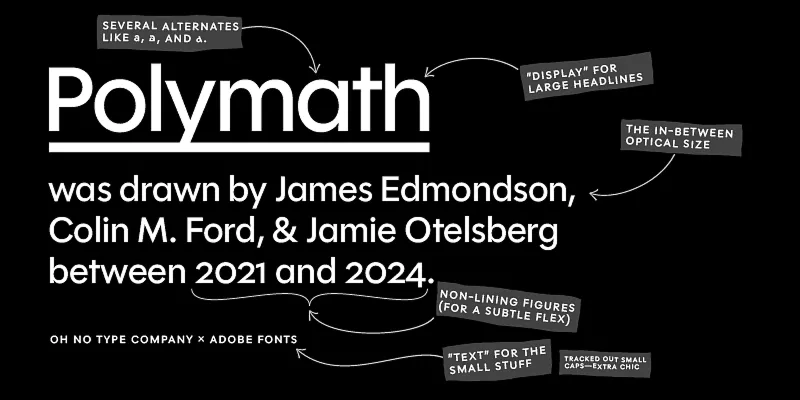
Font Tiếng Việt Polymath Black Font
Font Tiếng Việt Polymath Black Font – Font Đậm Mạnh Mẽ Cho Thiết Kế Nổi Bật
Polymath Black Font là lựa chọn cực kỳ phù hợp nếu bạn đang tìm một font chữ tiếng Việt dạng đậm (black) với phong cách hiện đại, cá tính và có độ “nặng” vừa đủ để tạo điểm nhấn mạnh cho tiêu đề. Nhờ nét chữ dày, chắc và đầy năng lượng, Polymath Black thường được dùng trong các dự án thiết kế cần gây ấn tượng nhanh như poster, banner quảng cáo, bìa mạng xã hội, hoặc nhận diện thương hiệu.
Polymath Black Font là gì?
Polymath Black là biến thể “Black” – tức độ đậm cao nhất trong hệ font, giúp chữ hiển thị rõ ràng ngay cả khi đặt trên nền phức tạp hoặc khi thu nhỏ trên các thiết kế digital. Font phù hợp khi bạn muốn:
• Tạo tiêu đề nổi bật trong poster/cover
• Thiết kế banner quảng cáo, thumbnail YouTube
• Làm logo chữ, slogan, headline landing page
• Dùng cho social content cần sự mạnh mẽ và rõ nét
Ưu điểm nổi bật của Font Tiếng Việt Polymath Black
• Nét chữ đậm “ăn tiền”: tăng độ tương phản, tạo cảm giác chuyên nghiệp, chắc chắn.
• Ứng dụng linh hoạt: phù hợp thiết kế thương hiệu, in ấn, social media, UI headline.
• Dễ phối font: kết hợp tốt với font sans mảnh/regular để tạo hệ thống phân cấp (typography hierarchy).
Gợi ý sử dụng Polymath Black Font trong thiết kế
Để Polymath Black phát huy tối đa hiệu quả, bạn có thể áp dụng các mẹo sau:
• Dùng cho H1/H2 hoặc headline chính, hạn chế dùng cho đoạn văn dài.
• Khi làm poster, ưu tiên tracking vừa phải để chữ “thở” và sang hơn.
• Phối với font chữ mảnh (Light/Regular) để tạo tương phản, giúp bố cục rõ ràng.
• Trên nền ảnh, thêm overlay nhẹ hoặc stroke mảnh để tăng khả năng đọc.